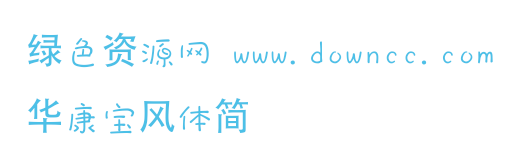
軟件介紹 軟件標簽: 華康字體 字體 華康寶風體簡體是一款敲可愛的字體。小編在網上苦苦搜羅了好久在找到呢~歡迎大家來綠色資源網下載華康寶風體簡軟件介紹今天小編為你帶來華康寶風體簡字體。這個字體看著圓滑,看上去萌萌噠,非常適合廣告設計、平面設計、印刷包裝、正文標題等人員使用。華康寶風體簡安裝說明方法一:控制面板/字體/文件/安裝新字體方法二:直接將字體復制到C:\WINDOWS\Fonts方法三:針對win7系統(tǒng),用戶只需選中字體右鍵安裝即可華康寶風體簡體小編點評這是小編在方正喵嗚體后,看到的最可愛的字體啦~ 軟件截圖 上一張下一張(1 / 1) 安裝詳細截圖 其他版本下載 標題 大小 更新日期 下載 下載地址 電腦版 華康寶風體簡體字體 點擊報錯 軟件無法下載或下載后無法使用,請點擊報錯,謝謝! 關閉報錯反饋 請描述您所遇到的錯誤,我們將盡快予以修正,謝謝! *必填項,請輸入內容 本類最新 華康漆隸體繁w5 wow魔獸世界華康少女字體ttf 免費版 華康蕓風體w3 繁體 華康pop2體w9 p 華康粗黑體繁 dfpyuanw7字體 ttf版 相關文章 Photoshop字體安裝使用方法和技巧 如何解決“無法新增字體”問題 Win 7系統(tǒng)安裝字體方法 網頁字體大小設置方法 怎么改網頁字體大小 在Linux系統(tǒng)中安裝字體的幾種方法 windows7字體顯示問題:打開某些程序的時候顯示的是亂碼 用戶評論 熱門評論 最新評論 第 1 樓 中國Downcc.com客人 發(fā)表于: 2018/07/05 13:33:48 很好,很喜歡 支持(0) 蓋樓(回復) 發(fā)表評論 查看所有評論(1) 昵稱: 請不要評論無意義或臟話,我們所有評論會有人工審核. 字數(shù): 0/500 (您的評論需要經過審核才能顯示)